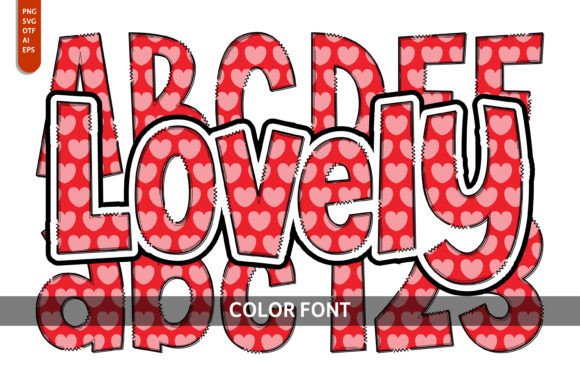
Hattachy Modern Handlettering
Baik Anda membuat produk POD (Print on Demand), undangan pernikahan, atau grafis media sosial, Hattachy Modern Handlettering adalah pilihan yang sangat ideal.